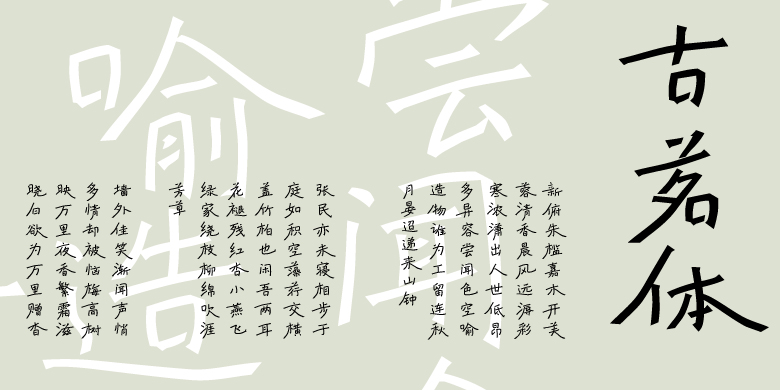
古茗体
创意书写
古茗携手方正字库,以制茶工艺为设计脉络,一场以笔墨为料、数字为火的 “炼字” 之旅就此展开 ,萃取手写笔触的鲜活灵动,经数字化提纯塑形,再融入黄庭坚书法 “一波三折” 的写意风骨,终淬炼出一套带呼吸感、可细品的古茗体,让字里行间皆藏茶饮般的松弛质感。
这款字体提供Regular、Bold两款字重,适合应用于新中式、古风等营销场景。